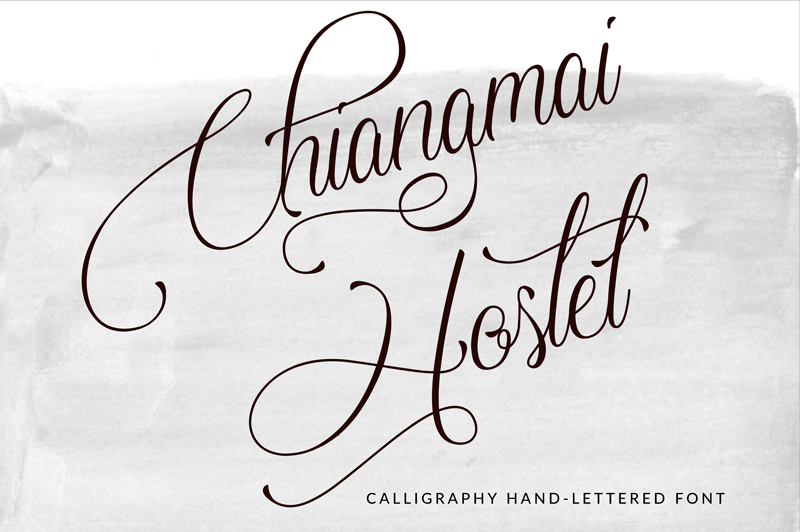
Descubra uma nova fonte para seus projetos criativos com a Chiangmai Hostel Font. Desenvolvida por Suthi Srisopha do estúdio Typhoon Type, essa elegante tipografia escrita à mão é ideal para aqueles que buscam adicionar um toque de ternura aos seus trabalhos. Esse font se destaca especialmente para quem precisa personalizar seus projetos com uma sensação mais suave e delicada. Perfeito tanto para títulos quanto para logotipos, cartões de convite, certificados e etiquetas, a Chiangmai Hostel Font também é perfeita para pequenos textos. Se você está procurando por uma fonte que seja não apenas visualmente atraente, mas também funcional em diversos tipos de projetos, então a Chiangmai Hostel Font pode ser o seu próximo amigo. Não hesite em adicionar um pouco de sua personalidade e delicadeza à sua próxima ideia ou projeto com essa elegante fonte escrita à mão.